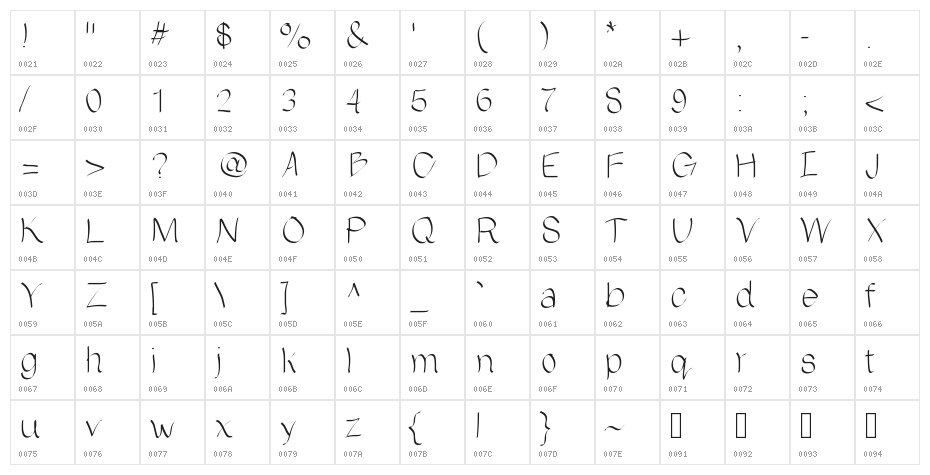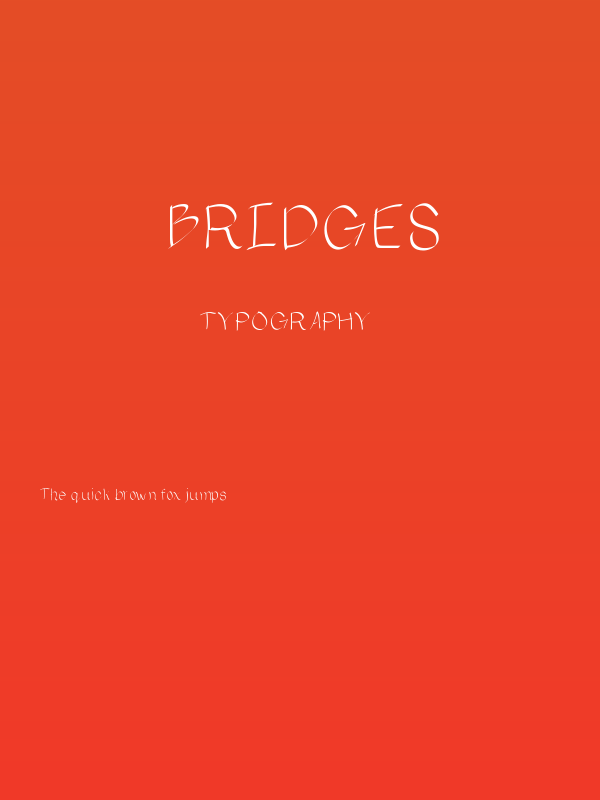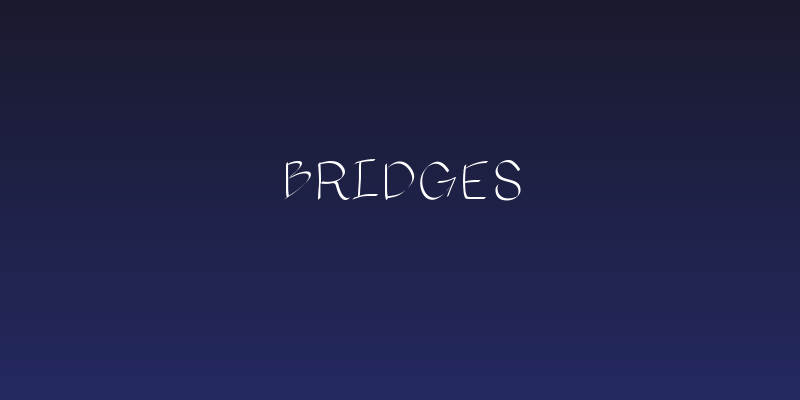
Bridges Font
| Stile generale | Modern, Artistic |
| Caso d'uso | Logos, Headlines, Creative projects |
| Progetti proposti | Ideal for greeting cards, invitations, artistic posters, and branding materials that require a personal and creative touch. |